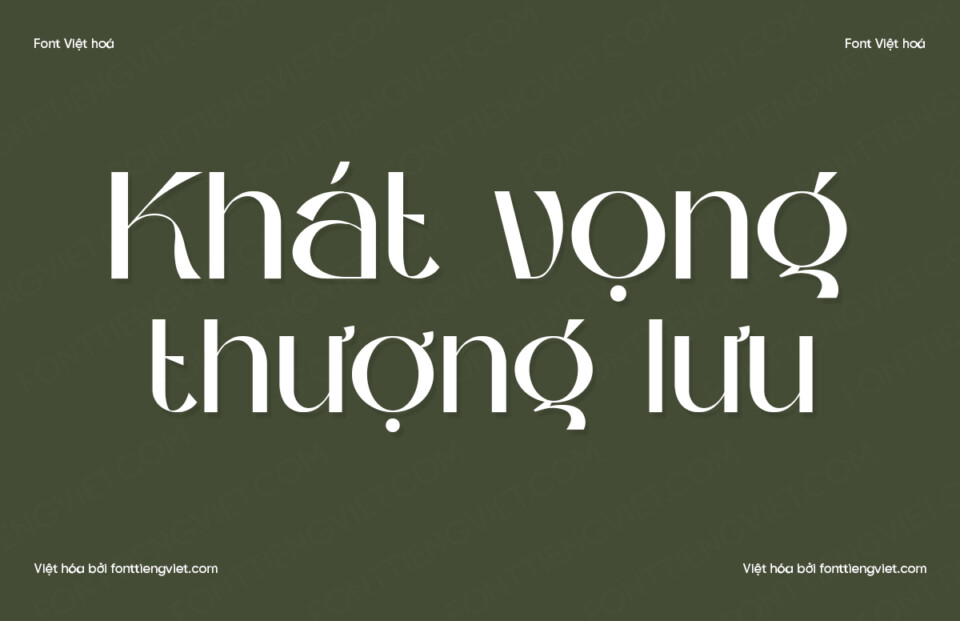
Font Việt hóa 1FTV VIP Amoria
Giới thiệu về bộ Font Việt hóa 1FTV VIP Amoria đẳng cấp
Trong thế giới thiết kế đồ họa hiện đại, việc lựa chọn một bộ Font Miễn Phí chất lượng luôn là ưu tiên hàng đầu của các nhà sáng tạo. Đặc biệt là Font Việt hóa 1FTV VIP Amoria, một siêu phẩm typography kết hợp hoàn hảo giữa nét cổ điển quý phái và tinh thần hiện đại. Đây là bộ font được cộng đồng thiết kế tại Việt Nam săn đón nhờ vào các đường nét thanh mảnh, uốn lượn tinh tế, giúp mang lại vẻ ngoài chuyên nghiệp cho mọi tác phẩm. Amoria không chỉ là một phông chữ thông thường mà còn là giải pháp tối ưu để nâng tầm giá trị thẩm mỹ cho các dự án sáng tạo từ cá nhân đến doanh nghiệp.
Những đặc điểm nổi bật của Font Việt hóa 1FTV VIP Amoria
Thiết kế tinh xảo và đa dụng
Font Việt hóa 1FTV VIP Amoria sở hữu hệ thống glyphs phong phú với nhiều ký tự thay thế đặc biệt. Điều này cho phép người dùng tùy biến linh hoạt trong các thiết kế logo, thiệp cưới, hoặc bìa sách nghệ thuật. Điểm mạnh của bộ font này chính là sự cân bằng tuyệt đối giữa các khoảng trắng và nét chữ, giúp văn bản luôn giữ được độ hiển thị sắc nét dù ở kích thước nhỏ hay lớn. Sự tỉ mỉ trong khâu Việt hóa giúp các dấu câu tiếng Việt được đặt vị trí chuẩn xác, không gây cảm giác rời rạc hay lỗi font khi gõ văn bản dài.
Ứng dụng rộng rãi trong nhiều lĩnh vực
Với phong cách sang trọng, bộ font này cực kỳ phù hợp cho các ngành hàng cao cấp như thời trang, mỹ phẩm, và trang trí nội thất. Các bạn học sinh, sinh viên cũng có thể sử dụng Font Việt hóa 1FTV VIP Amoria để trình bày các bài thuyết trình, làm báo cáo thực tập hoặc thiết kế slide học tập để tạo ấn tượng mạnh mẽ với thầy cô. Khả năng tương thích tốt trên nhiều phần mềm từ Adobe Photoshop, Illustrator cho đến Canva hay Word giúp bộ font trở nên thân thiện với mọi đối tượng người dùng tại Việt Nam.
Tại sao bạn nên chọn Font Việt hóa 1FTV VIP Amoria?
Lý do lớn nhất khiến Font Việt hóa 1FTV VIP Amoria trở nên khác biệt chính là cảm xúc mà nó mang lại cho người xem. Nó tạo ra một không gian nghệ thuật nhẹ nhàng nhưng vẫn đầy quyền lực. Đối với các nhà thiết kế web, việc sử dụng font này cho các tiêu đề chính sẽ giúp trang web trở nên bắt mắt và giữ chân người dùng lâu hơn. Hơn nữa, quy trình cài đặt bộ font này vô cùng đơn giản, chỉ cần vài thao tác giải nén và cài đặt là bạn đã sở hữu ngay một công cụ thiết kế mạnh mẽ trong máy tính của mình.